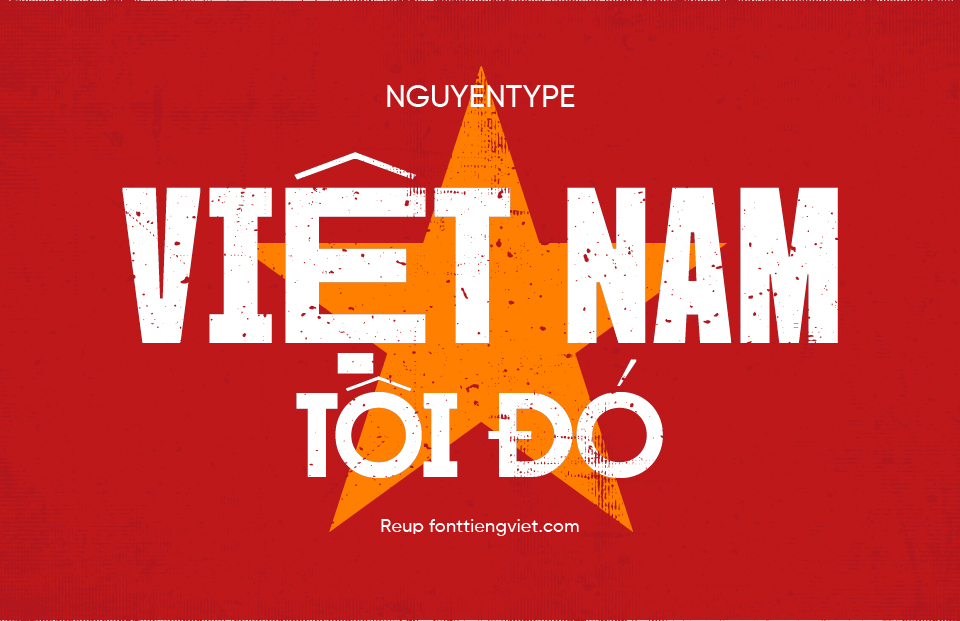
Giới thiệu về bộ Font tiếng việt NGT Vina Sans
Trong lĩnh vực thiết kế đồ họa và soạn thảo văn bản, việc lựa chọn một Font Chữ phù hợp đóng vai trò quan trọng trong việc truyền tải thông điệp. Font tiếng việt NGT Vina Sans là một trong những bộ font hiện đại, được tối ưu hóa riêng cho người dùng Việt Nam. Với thiết kế không chân (sans-serif) thanh lịch, bộ font này mang đến sự tối giản nhưng không kém phần tinh tế. Đây là sự lựa chọn lý tưởng cho các bạn học sinh, sinh viên khi làm bài thuyết trình, báo cáo hoặc dự án sáng tạo cá nhân tại trường học.
Đặc điểm nổi bật của Font tiếng việt NGT Vina Sans
Điểm mạnh nhất của Font tiếng việt NGT Vina Sans chính là khả năng hiển thị cực tốt trên các thiết bị kỹ thuật số. Các nét chữ được thiết kế cân đối, khoảng cách giữa các ký tự được tính toán kỹ lưỡng giúp người đọc không bị mỏi mắt. Đặc biệt, bộ font này đã được Việt hóa hoàn chỉnh, hỗ trợ đầy đủ các dấu câu trong tiếng Việt mà không xảy ra hiện tượng lỗi font hay nhảy ký tự khi gõ trên bảng mã Unicode thông dụng.
Cách ứng dụng Font tiếng việt NGT Vina Sans hiệu quả